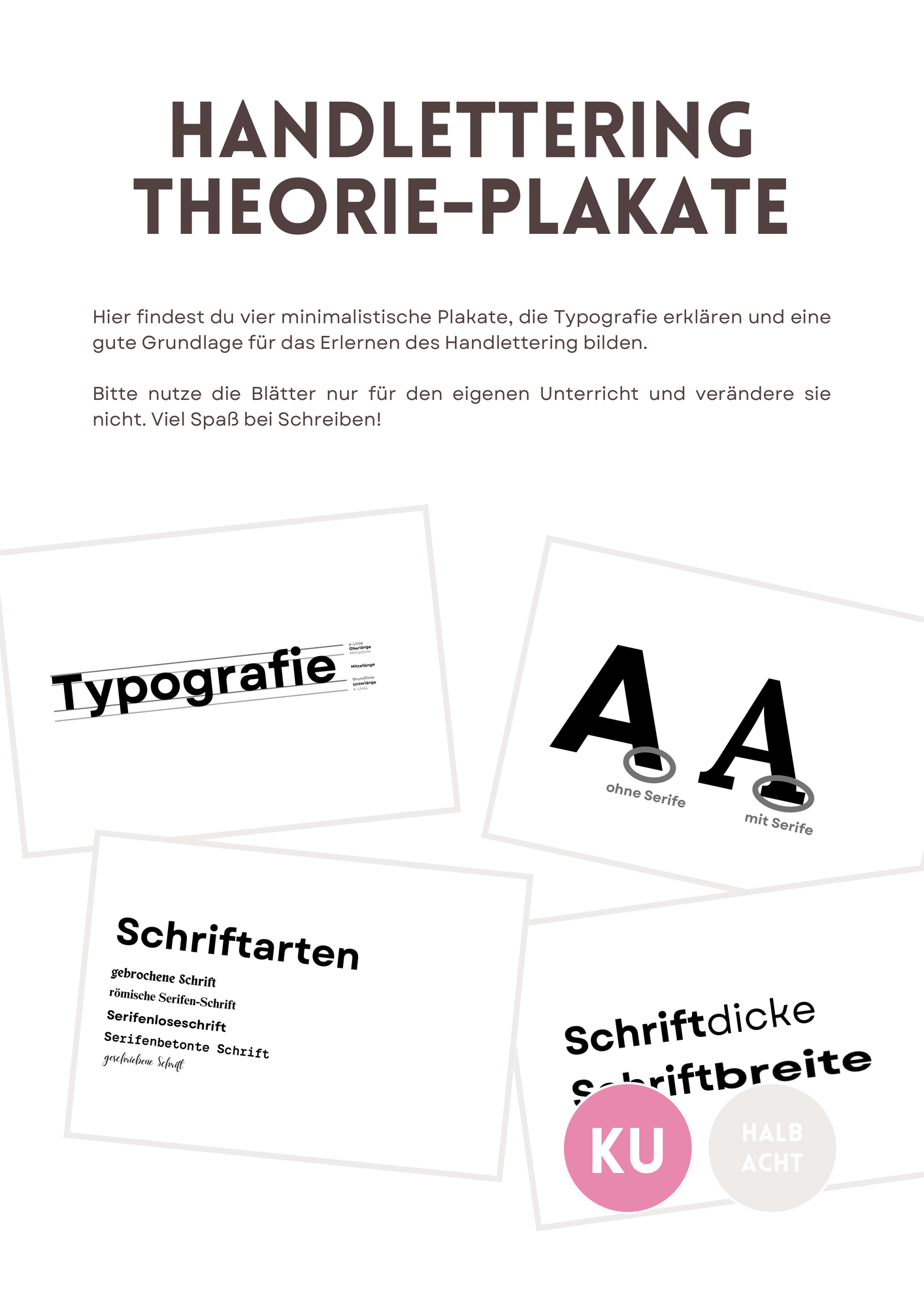
Poster - Handlettering, Plakate, Grundlagen Typografie - halb acht - Deckblatt
Handlettering Theorie-Plakate
Entdecke vier minimalistische Plakate, die die Grundlagen der Typografie erklären. Diese Plakate bieten eine tolle Basis für das Erlernen des Handletterings. Sie sind ideal für den Unterricht und helfen deinen Schüler*innen, die verschiedenen Schriftarten und -stile zu verstehen.